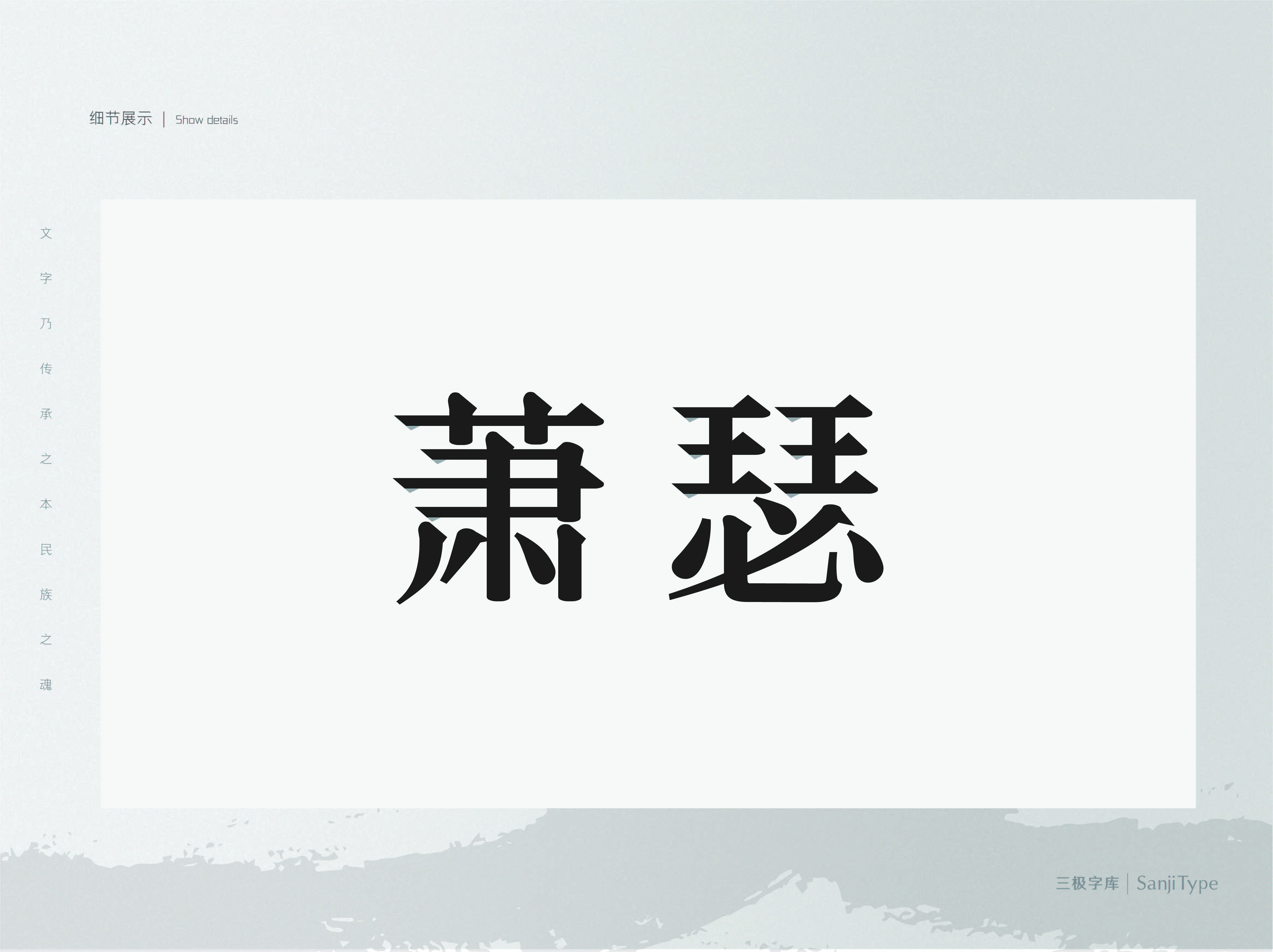
三极萧宋简体家族
三极萧宋简体系列:整体笔画偏细,字形结构饱满,笔锋简洁流畅。庄重典雅,结合于宋体本身,能够显现出字体的高雅而不浅俗的特点。这款字体运用非常的广泛,不仅适用于标题和正文排版,还适用于报刊杂志,书刊、品牌广告和产品包装设计。
适用媒介:杂志、书籍、广告、标志、宣传册、包装、影视、动漫、交互设计。